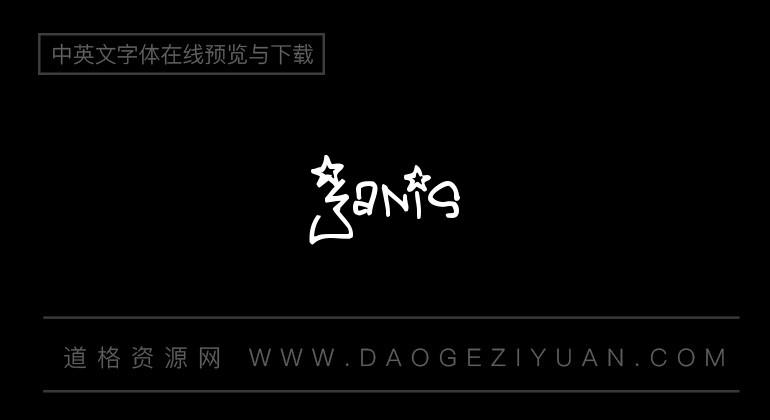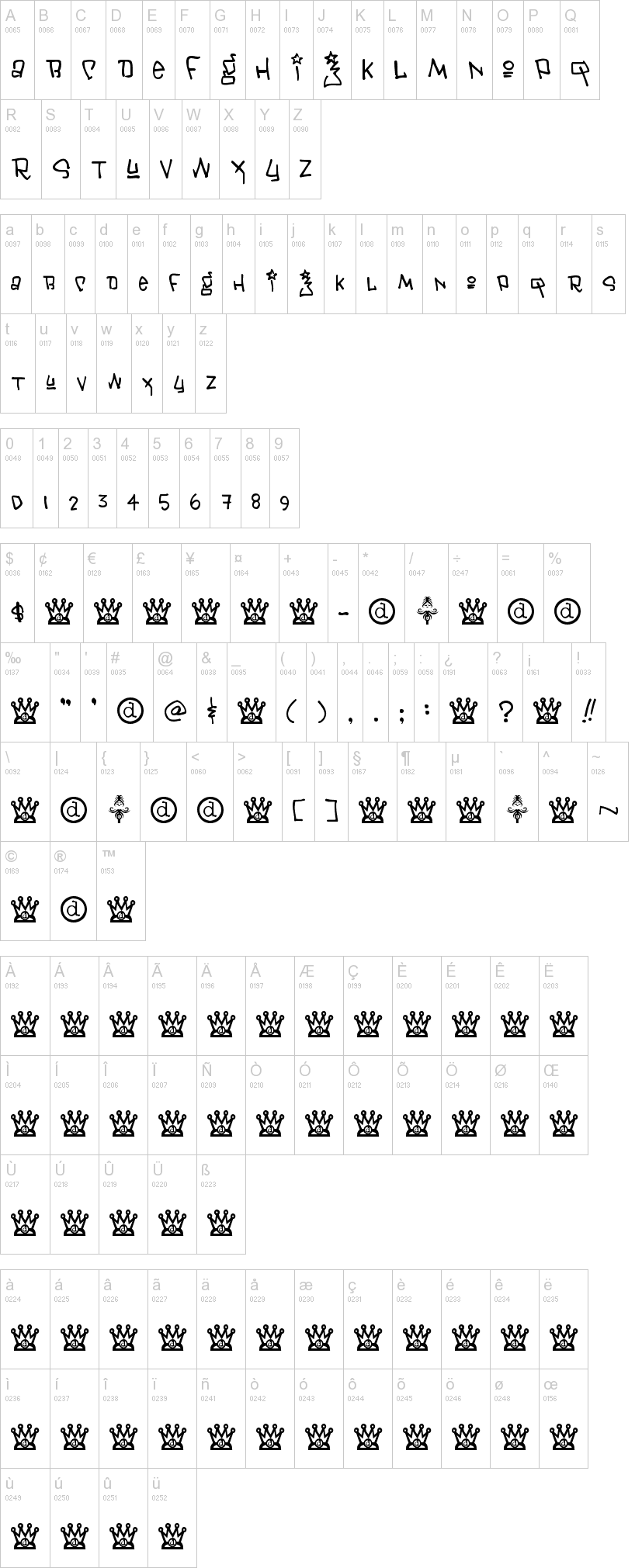
Janis是一种现代手写风格的字体,由于其优美和自然的笔画而备受欢迎。它的笔画流畅、轻盈,具有良好的可读性。Janis字体设计的初衷是迎合现代手写风格的需求,它的字母看起来像是由一支熟练的钢笔写出来的,具有一种独特的魅力和个性。 Janis字体的设计者是一位名叫Elena Genova的保加利亚设计师。它最初发布于2018年,迅速受到了设计师和艺术家们的喜爱。Janis字体包括两种不同的字重,可以用于多种设计应用,如文本、标志、海报、卡片等等。 总体来说,Janis字体是一种优美、自然、流畅的现代手写字体,适用于多种设计应用,是设计师们的不二选择。内容介绍
Janis是一款非常不错的手写艺术字体,具有很好的视觉感,适合于文化类的宣传设计、商业类品牌的广告和产品包装设计以及个性化文字排版等较多场景。